神的字体会跳舞,来看这个日本设计师
Takashi ohashi
大橋 史のCG动画字体创作
大橋史,动画导演、艺术总监,1986年12月出生于东京,2012年毕业于多摩美術大学 大学院美術研究科情報设计专业,他发布了顾及CG的有限性与无界限的动画表现作品。作为导演参与了米津玄师的《春雷》影像制作、艺术家QueHouxo等文化色彩浓厚的项目。他的许多作品被刊登或上映于 Stash、motionographer、onedotzero、cartoonbrew、theCreators Project 等国内外设计文化相关杂志和电影节上,并得到了很高的评价。
花譜 - 戸惑いテレパシー(柊キライRemix)
フレデリック - フレデリズム2 全曲トレーラー
西尾維新大辞展 - バトルシーン
大橋史常年与日本明星舞台合作,擅长文字与CG动画的结合律动设计,他制作的作品曾获奖DOTMOV FESTIVAL、MEC AWARD、ANIMATED DREAMS、London International Animation Festival、2016新千岁机场国际动画金奖等等。
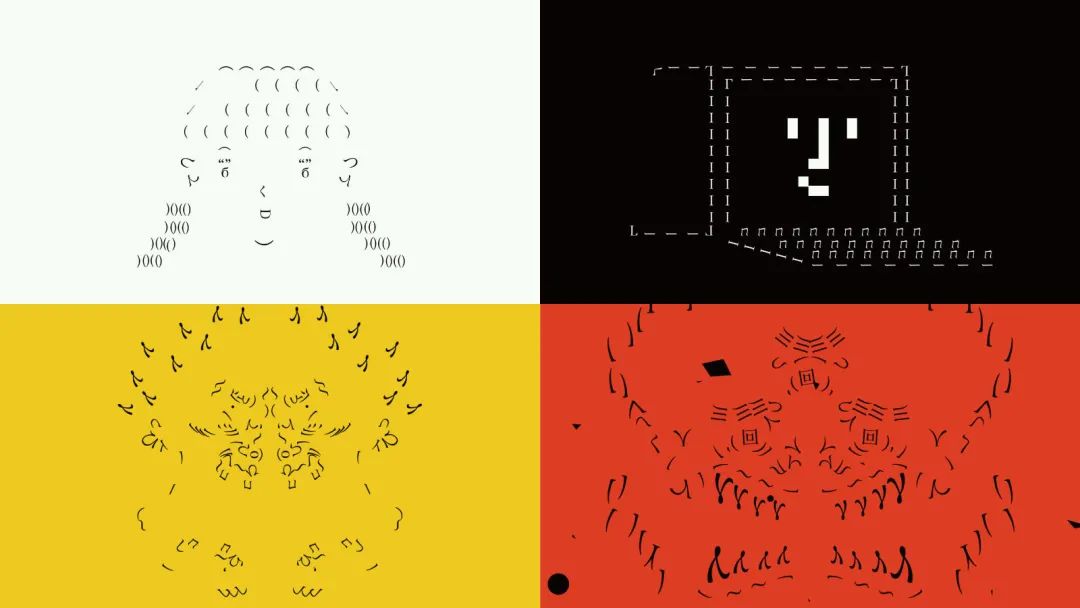
CHANNELER
BURNOUT SYNDROMES - 文學少女
BURNOUT SYNDROMES文學少女
BURNOUT SYNDROMES文學少女是大橋史最知名的作品之一,将BURNOUT SYNDROMES乐队主唱熊谷先生的真实经历主题形象化"痛苦的校园生活经历逐渐促成了我自己的艺术创作"。由于歌曲有文艺的主题,所以使用抒情的方式来解构元素排版,重构字体和字母图形,装饰字母和涂鸦设计。
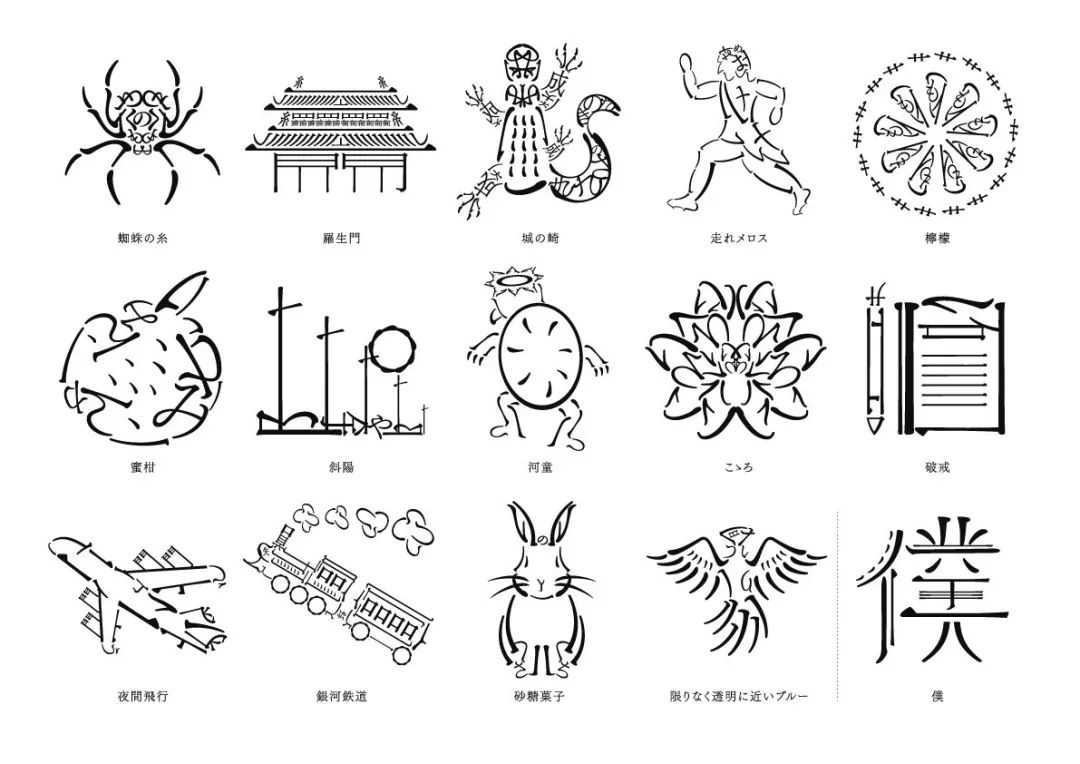
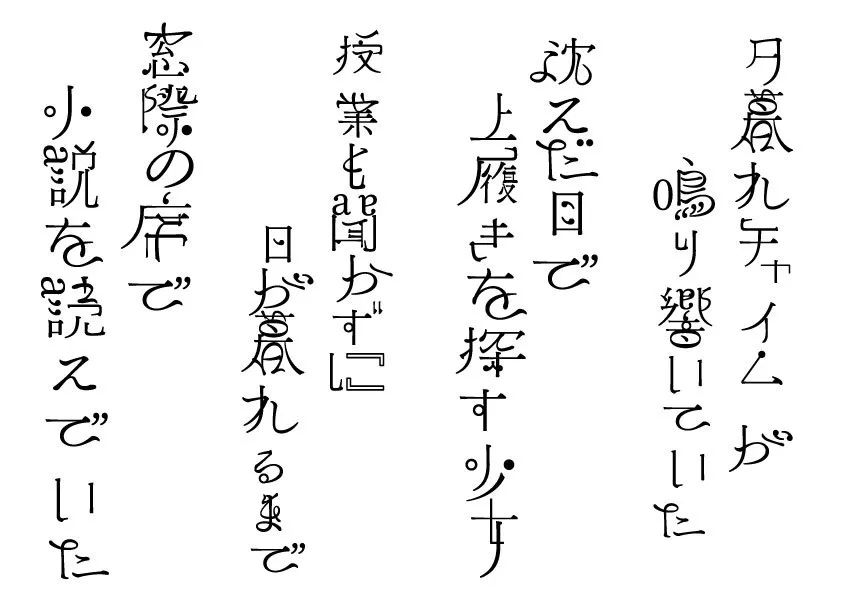
一些字符象形文字
文字设计在大桥史的作品中很常见,他大多数作品都像一部以字体为演员的音乐表演。不论质还是量都让人叹为观止。我们甚至来不及去对某一个分镜驻足欣赏,就被淹没在了创意的湍流中。这种赶脚,看截图是体会不到的!下面看一视频感觉一下~
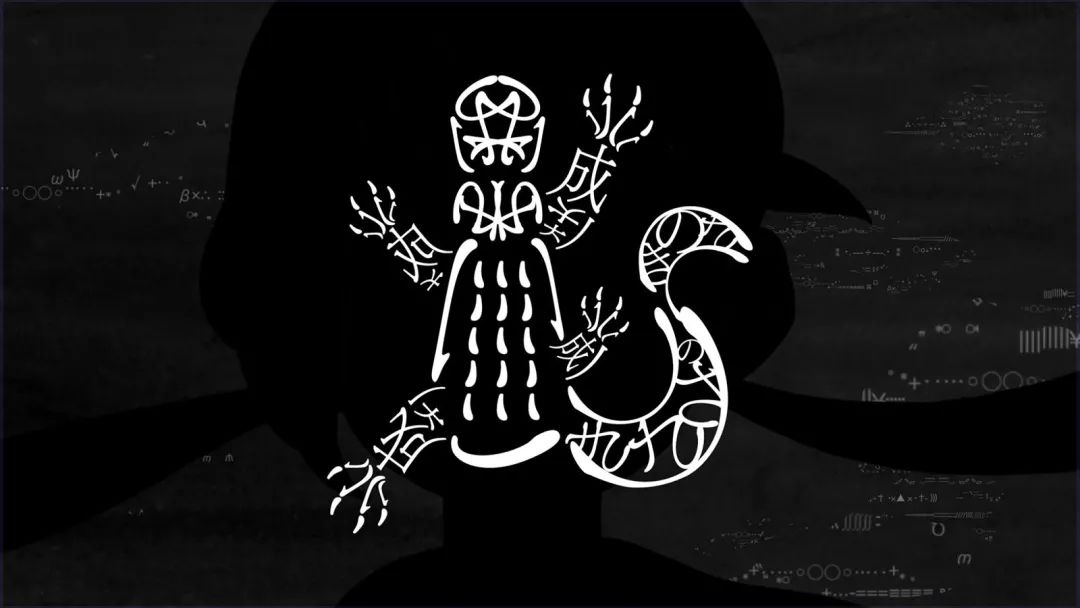
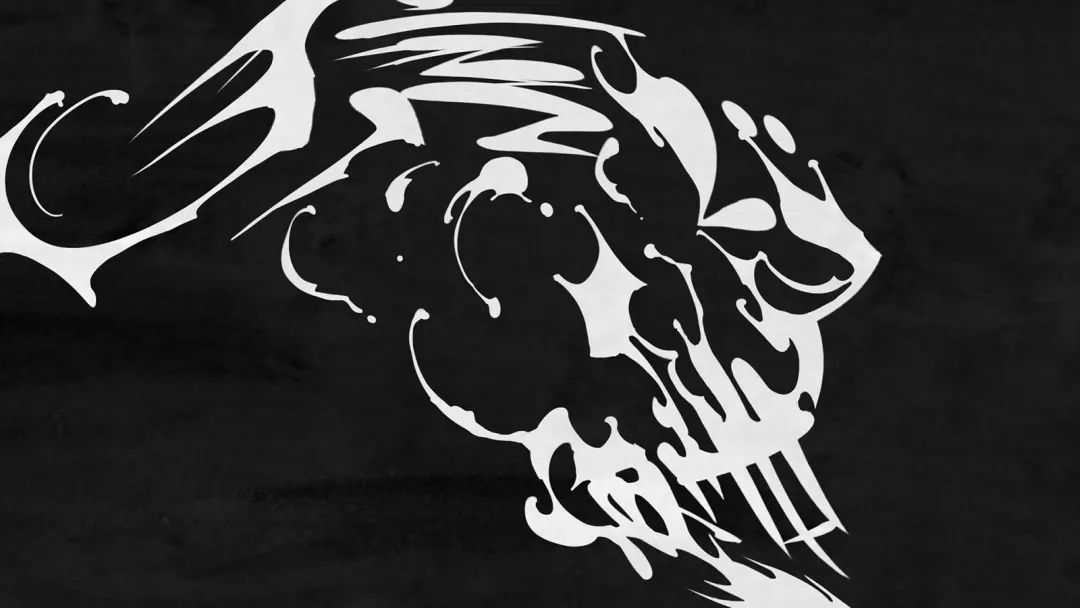
金子開発
在一个视频作品中使用不同艺术风格动画流程,是受到了livetune的"转移"潮流的影响。这个想法是把一套统一的艺术材料扭曲成一个具有不同世界观的空间,但文阁书院却反其道而行之。想法是,即使在触感上有差异,如果对每一层的绘图数据(配色方案)应用统一的外观,绘图的差异也不会残留为一种不好的不适。
复合加工
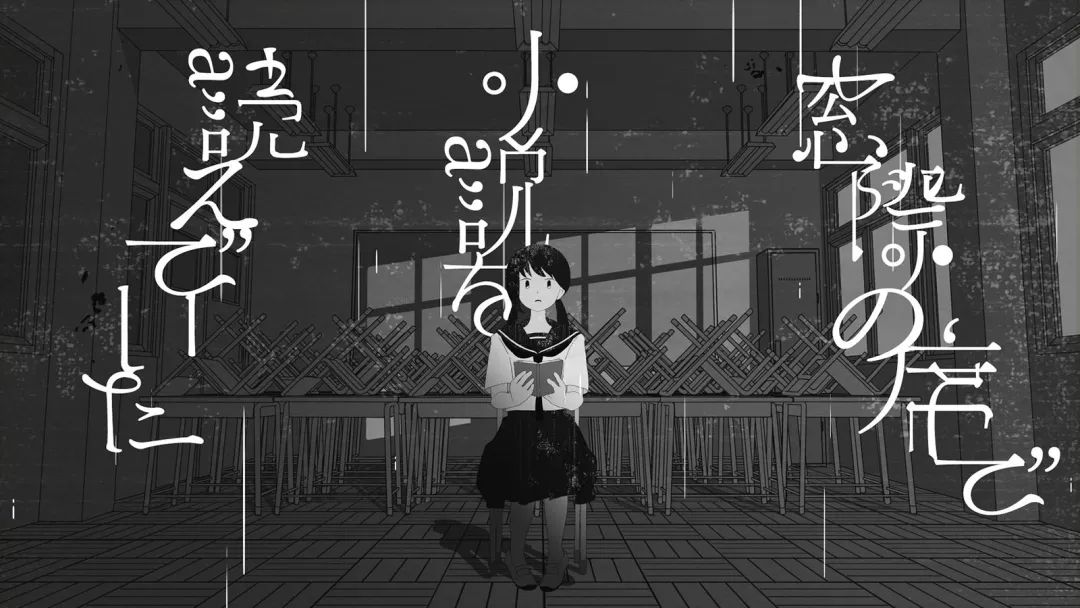
拆卸并重建字体
西尾維新大辞展 - バトルシーン
利用影像装置作品【战斗场景】原故事系列中绘制的 "主人公岚木小美与妹妹凯伦的打斗场面 "的文字,单单是排版就提供了沙夫特绘制的动漫场景的真实感,通过物理计算和After Effects的复合处理,大量的角色干扰了动漫的动作。我的目标是赋予它一个独特的克伦奇玛,并以排版元素描绘的阿拉木和凯伦的出现给观众带来惊喜。这种文字拆分结合动漫人物形象的设计真令人惊叹~
文字构成人像
使用物理学的运动图形,视频中使用的字体相对于屏幕来说也被布置得很小,以形成一个1600字的屏幕,符合"展览空间在一本巨大的字典里"的计划"。对于战斗场面,采用了物理计算的方式,但如果单靠电脑计算来制作画面,就会失去日本动画中最精彩的"克难",所以用电脑通过延时图的编辑和分帧来补充每秒60帧(fps)的画面与和手势动作都要造成激烈的战斗。
片段部分截取
对于角色从天花板上掉下来的场景,使用了Newton2为基于物理学的动画创建关键帧,然后使用时间图和帧插值进行前期合成,以重新创建动画的角化。
物理演算を使ったモーショングラフィックス
CHANNELER
言語学の研究
这部动画的主题是"语言的转变",描绘了主人公在成长过程中对文字的痴迷,并从中获得智慧。画面上散落的人物和符号,以抒情的方式押韵,这也是HIPHOP的特色之一。而动画作品中,将主人公的生活ASCII艺术与抒情内容一起发展。为了引起人们对ASCII艺术随着每一句歌词的展开而发生的极简变化的关注,我们避免了深浅、平移等给人以透视感的镜头作业,强调画面的二维性,表达人物成画的趣味。
描绘过程中勾勒的草图
我和负责创作的Yuri Hafuka一起研究了随着人类发展而变化的语言。如上所示,随着年龄的增长,我们获得了更多的智慧,学会了从简单的语言到形容词、助词、连词,再到俚语,包括年轻人的词语。比如说童年—我,咖喱,我想吃(只用名词和动词的组合)童年—我想吃咖喱(加盟连接)青春期—我想吃超赞的咖喱(省略连接词后,将青春期的词加为形容词),成年—我想吃咖喱(用一个礼貌的词)如上图所示,我们发现一个有趣的现象,那就是每个短语可以使用的字数会随着说话人的年龄而变化。
展示
它的制作方式与原来在网格上输入哥特式比例字体制作的ASCII艺术不同。为了表达CHANNELER的故事,"一个痴迷于文字的人的故事",我想有意识地去表现日本浮世绘中的鬼怪等肉体形状。为此,我使用了可以用平野民谣打字的平野民谣字符和符号,这样就可以打出带有拐点的线条。使用平野敏草字体的ASCII艺术规则,勾勒完后不要拆开每个颈部,你可以自由地倾斜和翻转它,不要改变字符的长宽比。
左图:ASCII设计使用的明朝体体排列,右图:ASCII美术成品
フレデリック - フレデリズム2
全曲トレーラー
与平面设计师佐佐木俊(Shun Sasaki)合作,制作了日本摇滚乐队“弗雷德里克”的预告片。
增强歌曲节奏和图形的动作
为了把字体的轮廓和奇特的色彩表现出来,所以我想尽量减少色彩变化的效果,以及旋转和比例变化的节奏运动,以打乱布局。我使用了一个名为"CartoonMoblur"的插件来进行简单的水平、垂直和对角线运动,使角色的部分沿着动画的轨迹拉伸和收缩,与Fredrick有趣的水平节奏和佐佐木俊的图形相得益彰。
Art director: shun sasaki (AYOND)
花譜 - 戸惑いテレパシ
(柊キライRemix)
歌手Hanafu为docomo的下一代通信标准5G配合曲《Bewildering Telepathy》拍摄的MV,为了抓住下一代通信标准“5G”作为高速网络的隐喻,“Hanafu参与了VR赛车游戏”。像《WipeOut》、《RedOut》这样充满未来感的美术方向,以及反重力竞速游戏特有的极限竞速动作,计划打造一个未来互联网空间的形象。
在这支MV中,有意识地画出了两个视角。花火以第一人称视角,将自己沉浸在赛车游戏中,以此来隐喻未来的互联网空间,漫画的框架布局为第三人称视角,画面类似于桌面浏览器窗口。但为了加强音乐视频主题"互联网空间"的方向性,将框架布局做成类似于浏览器的窗口。
作为第三人称视角的桌面
搭配VR护目镜的比赛场景,是对下一代互联网空间的隐喻,也是对互联网空间沉浸式的第一人称视角。比赛现场的视觉效果是以《WipeOut》为蓝本。
比赛场景以第一人称视角
采用了人物身体的八字剪影,以及类似阿凡达的设计,打造了统一的八字剪影。在头像设计上,使用了象征互联网文化的图标(2ch ASCII艺术蒙娜、Vaporwave石膏像、emoji图案等),绘制了一个有趣的比赛场景。
以数字空间为中心打造外观
Cokiyu - Your Thorn
日本电音人cokiyu的歌曲《你的荆棘》MV,以"重复理论"为主题,将白噪音和威斯康星的声音唱腔视觉化,让人联想到胎儿的记忆,也让人联想到cokiyu音乐中圆润厚重的电子乐。他创造了动画。影片描写了追寻生命进化的画面,以及对生命的执着。影片中的生物是对称的、象征性的,就像恩斯特-海克尔的植物艺术一样,我们希望引起人们对其视觉美感的关注。